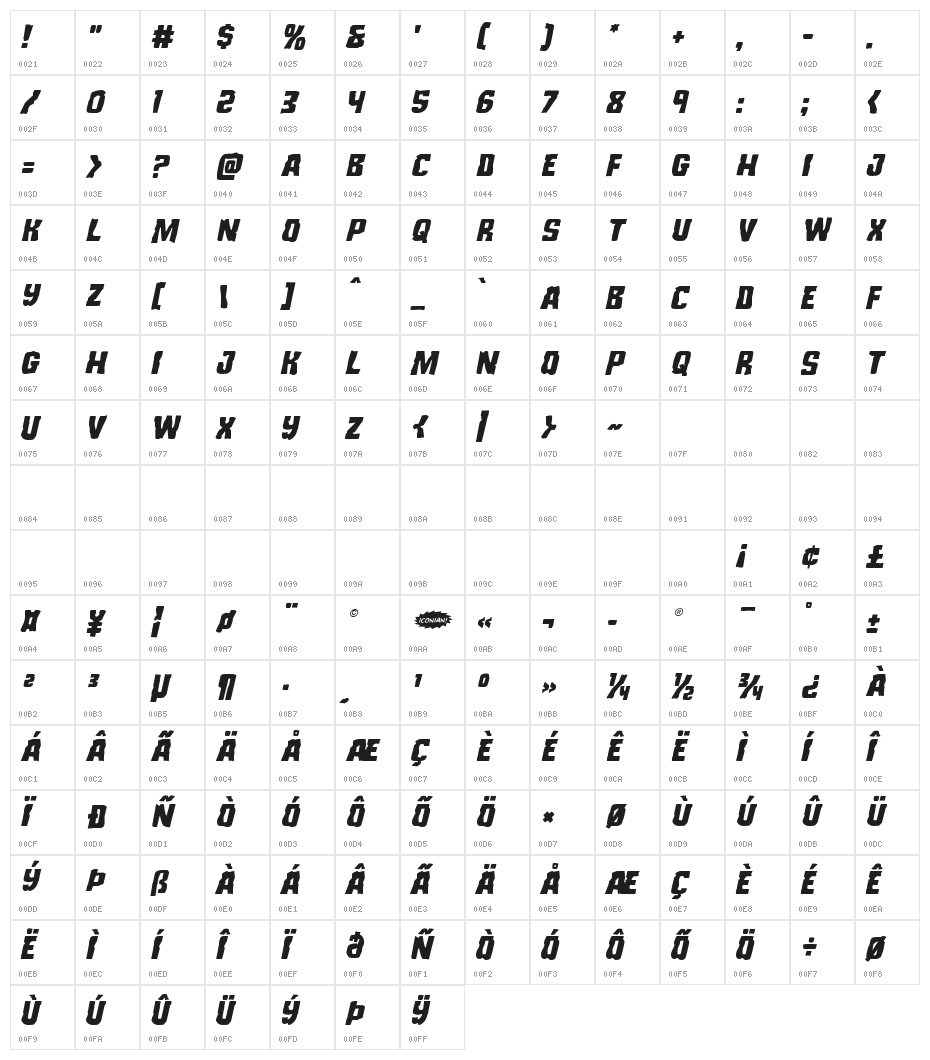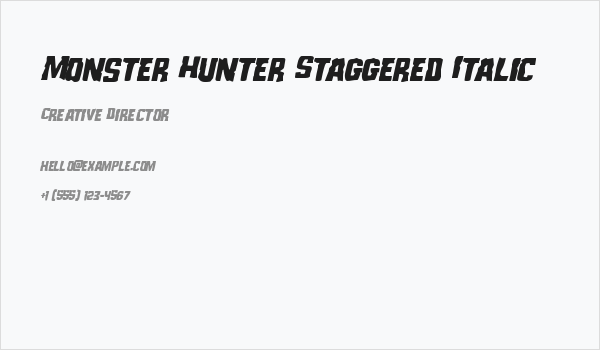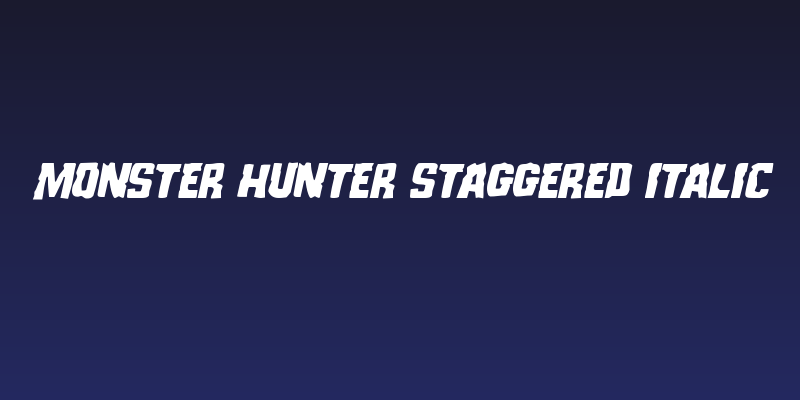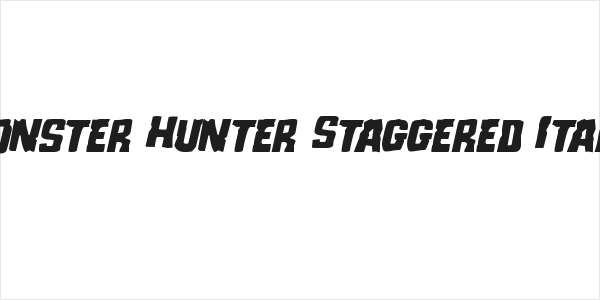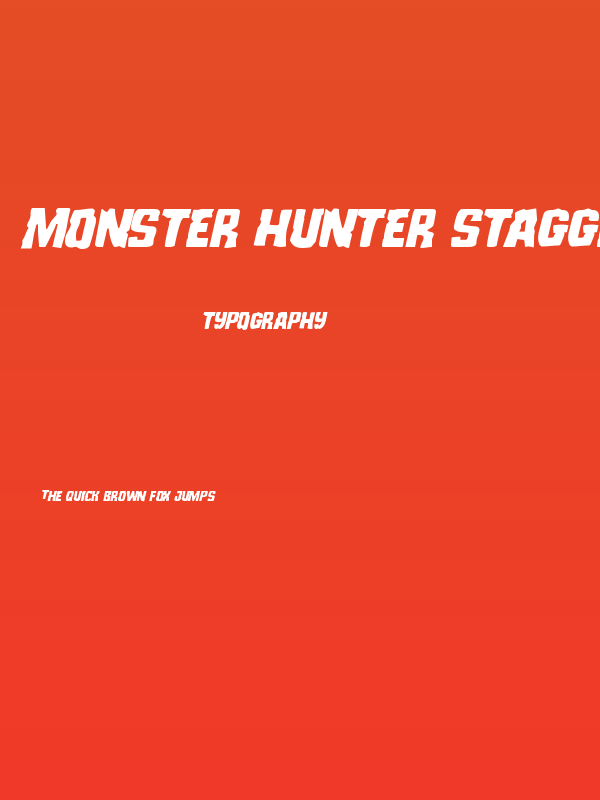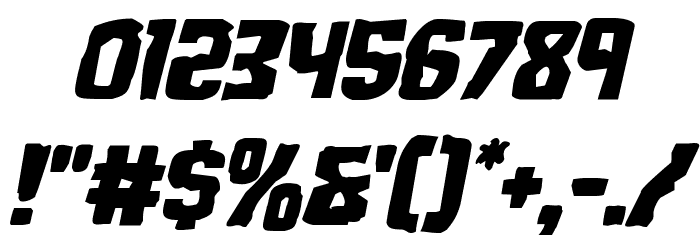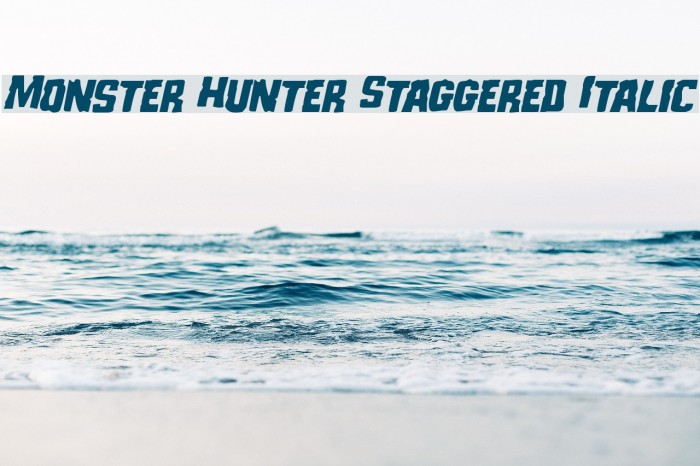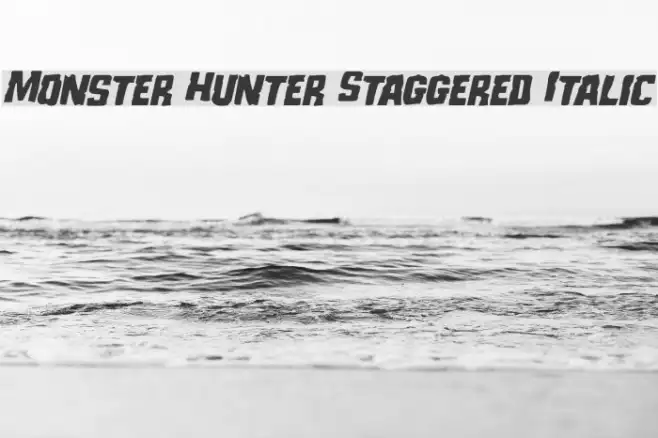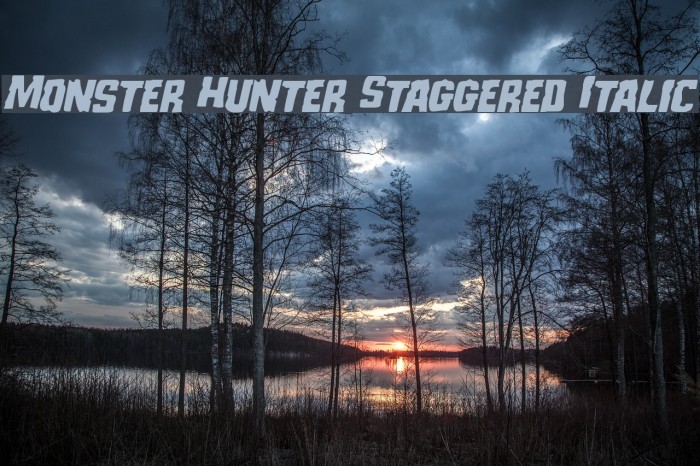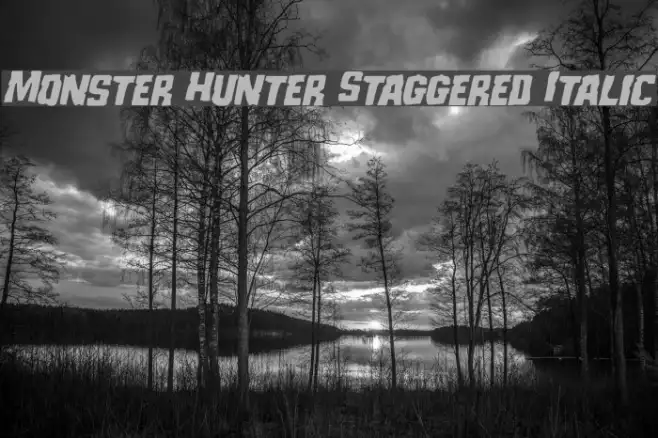
Monster Hunter Staggered Italic Font
✎ Thick
| Vorgeschlagene Projekte | Ideal for video game titles, movie posters, sports branding, and dynamic advertising campaigns. |